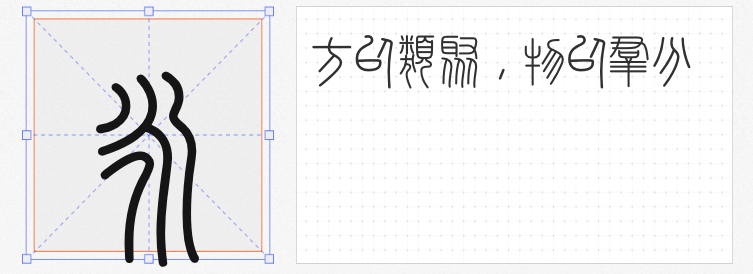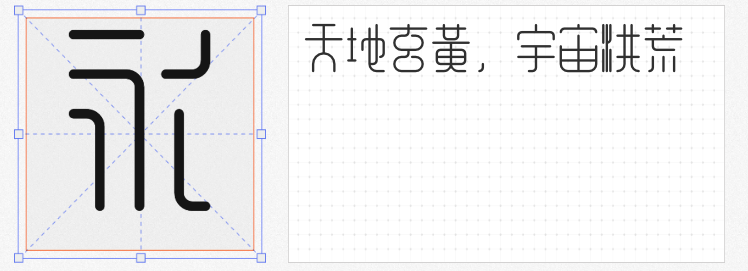
在品牌视觉与文化创意领域,书法字体以其独特的艺术表现力成为设计师的“秘密武器”。本文精选四款免费商用书法字体,涵盖楷书、篆书、小篆简化体等类型,兼具实用性与艺术价值,助力设计师突破创意边界。
由设计师黄煜臣创作的江西拙楷,以自然斑驳的肌理与手写痕迹打破电脑字体的冰冷感。其笔画粗细不一、连笔断点随性,赋予文字“未完成”的拙朴气质,尤其适合文创产品包装、古风海报及短视频字幕。该字体支持多平台调用,9.46MB的轻量化设计适配各类设计软件,为品牌注入人文温度。
余繁新语 Medium将秦小篆的对称美学与现代设计语言融合,通过简化字形提升辨识度。其圆润笔画与几何化结构,既保留篆书的秩序感,又赋予文字更强的视觉冲击力。该字体在电商海报、标志设计中表现突出,例如中医品牌“春林堂”以余繁新语为LOGO,既传递传统医学的庄重,又通过圆润笔画弱化距离感,契合轻古风审美趋势。
基于演示春风楷与演示秋鸿楷的开源拓展,寒蝉书体·春秋 春风通过优化西文字符大小、调整字偶距、补全通用字,实现中英文字体的和谐统一。其保留了手写楷体的自然笔触,同时强化竖向排版适配性,适用于书籍封面、展览海报等需要文化深度的场景。SIL Open Font License 1.1授权保障商用无忧。
由咸阳职业技术学院学生团队开发的峄山碑篆体,以秦代《峄山刻石》为蓝本,通过数字化技术还原李斯篆书的“玉箸”笔法。其线条圆融敦厚、结构上密下疏,单字对称性极强,适合文化机构LOGO、博物馆展览设计等场景。该字体既承载了“书同文”的历史记忆,又以现代技术延续篆书的生命力,是传统文化与数字创意的完美结合。
从江西拙楷的手写温度到峄山碑篆体的历史厚重,这四款字体以多元风格满足不同设计需求。它们不仅是工具,更是文化符号的载体。设计师可根据品牌调性自由选择,让文字成为传递价值观的视觉语言。